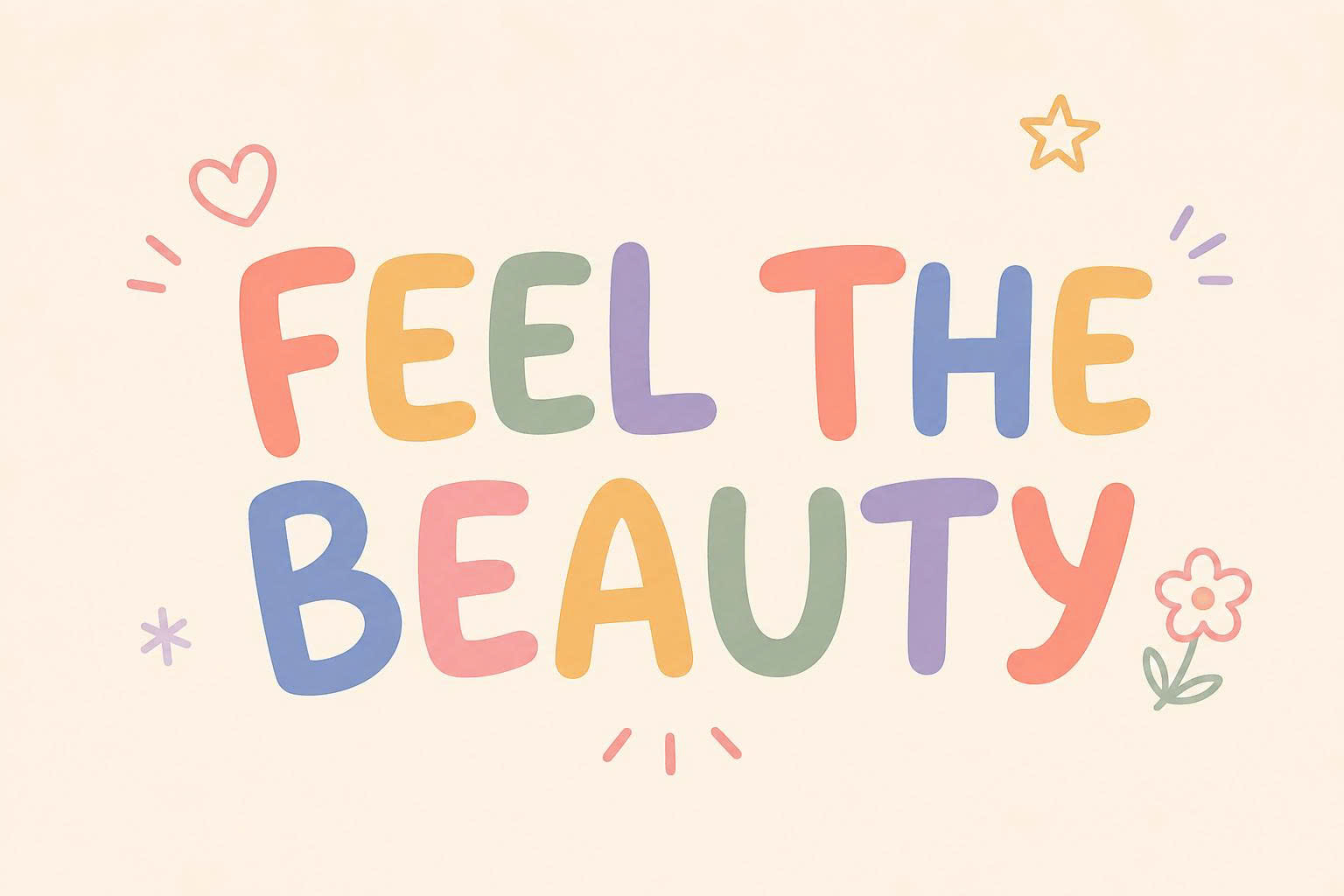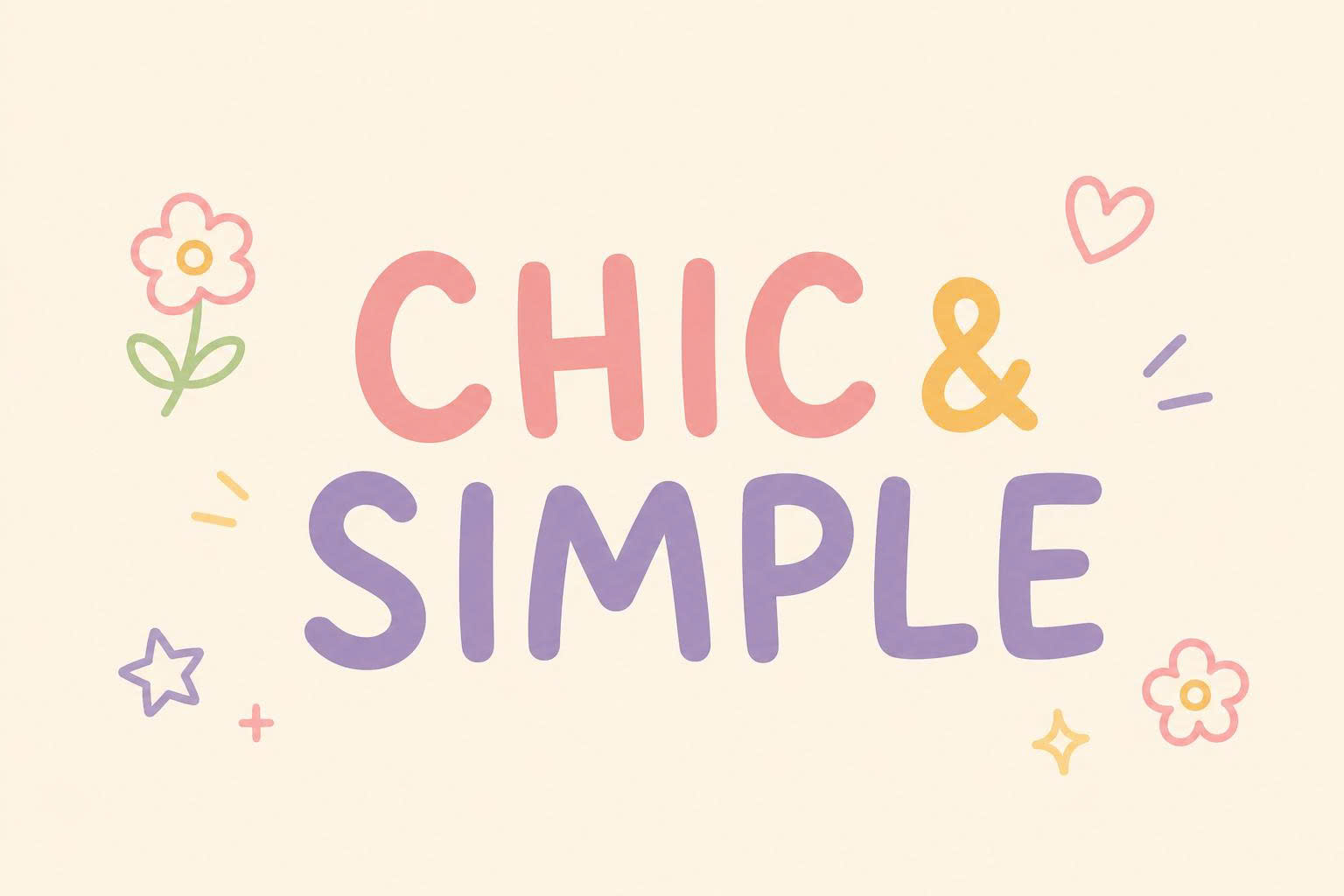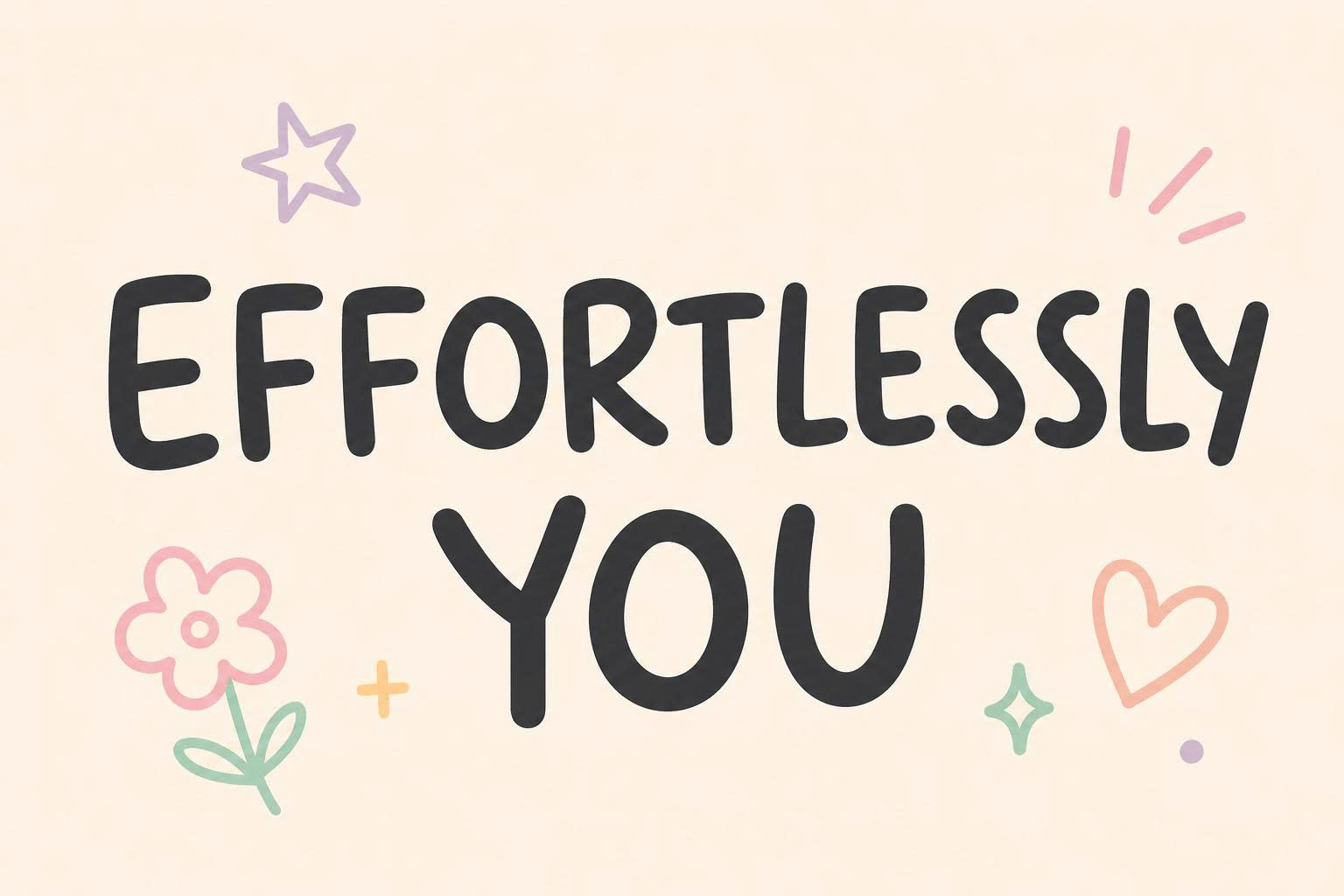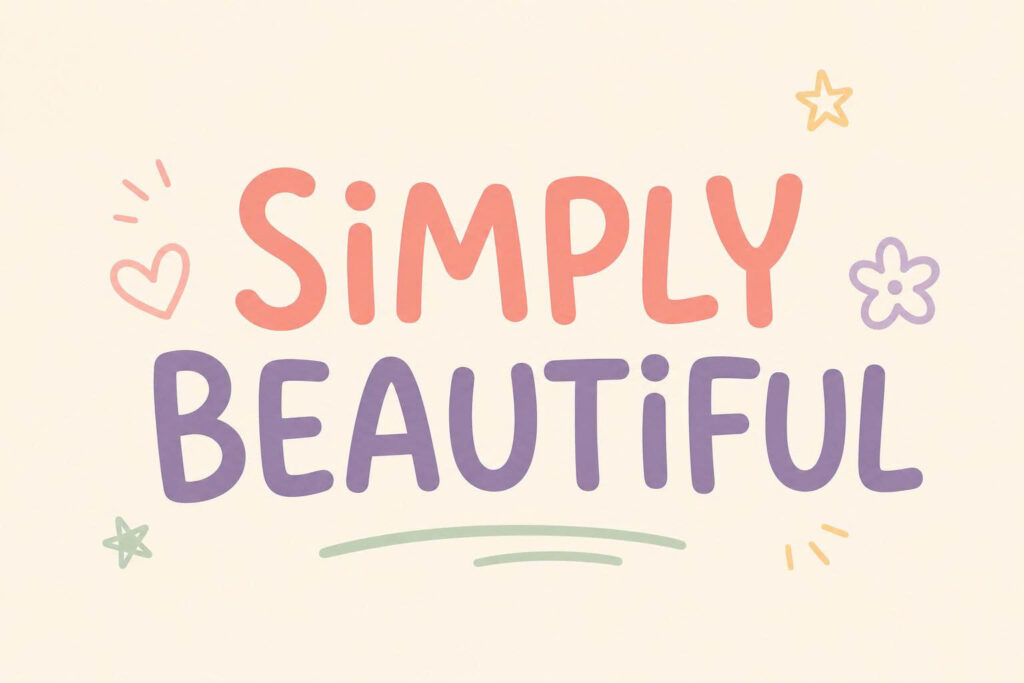
One Little font Việt hóa là bộ phông chữ thuộc dòng Casual Handwritten mang phong cách ngây thơ, mô phỏng sinh động nét viết tay nắn nót của con trẻ trên những trang giấy vẽ thủ công. Với tỷ lệ chữ nhỏ nhắn, các đường bo tròn mềm mại và nhịp điệu chữ tự do, Little One Font là chất liệu trực quan tuyệt vời để các kiến trúc sư, nhà thiết kế mang lại cảm giác ấm áp cho các bản vẽ phối cảnh trường mầm non lắp ghép, phòng ngủ trẻ em hay biển hiệu homestay dành cho gia đình.
Tỷ lệ nhỏ nhắn mộc mạc và nét hồn nhiên của One Little font Việt hóa
Điểm cuốn hút của One Little font Việt hóa nằm ở sự bất đối xứng nhẹ nhàng giữa các con chữ, tạo cảm giác như những lời thủ thỉ yêu thương được ghi chép vội vàng nhưng tràn ngập cảm xúc. Cấu trúc chữ sở hữu độ dày nét thanh thoát, các góc cạnh được gọt tròn mịn màng giúp loại bỏ hoàn toàn sự nghiêm nghị của các khối nhà xây dựng công nghiệp.
Sự ổn định về mặt cảm xúc của dòng font này giúp khơi gợi tình cảm gia đình, sự nâng niu và bầu không khí bình yên trong tổ ấm. Khi kết hợp cùng các vật liệu kiến trúc thân thiện như gỗ thông mộc, vách panel sơn màu pastel, thảm nỉ êm ái hay tường kính đón sáng tự nhiên trong các căn nhà lắp ghép nghỉ dưỡng, One Little Font tạo nên sự hòa quyện thẩm mỹ vô cùng dịu dàng.
Tư vấn từ chuyên viên: One Little Font sở hữu cấu trúc con chữ khá nhỏ và nét thanh thoát. Để bản thiết kế đạt hiệu quả thẩm mỹ tốt, bạn nên sử dụng phông chữ này cho các tiêu đề phụ, câu nhắn gửi yêu thương hoặc tên góc học tập.
03 Ứng dụng Little One Font vào công trình thực tế
Nhờ vẻ ngoài ngây thơ và tính gợi cảm xúc gia đình phong phú, bộ phông chữ này mang lại giá trị thực tế lớn trong khâu tạo điểm nhấn cho các công trình hiện đại:
- Hệ thống biển tên phân khu Trường Mầm non Lắp ghép: Những nét chữ nhỏ nhắn của Little One Font rất ăn ý khi gia công chữ nổi bằng gỗ sáng màu hoặc in decal dán tường, giúp các lớp học mầm non toát lên vẻ ấm cúng và tạo sự an tâm cho phụ huynh khi gửi gắm con trẻ.
- Bảng tên phòng và Biển chào mừng Homestay Gia đình: Phông chữ này khi khắc chìm trên các tấm gỗ pallet mộc sẽ giúp các căn phòng nghỉ dưỡng toát lên nét ngọt ngào, tạo nhiều góc chụp ảnh kỷ niệm ấm áp cho du khách.
- Trang trí góc đọc sách và Không gian phòng ngủ của bé: Bạn có thể dùng One Little font Việt hóa để làm bảng nội quy thân thiện, nhãn dán đồ dùng học tập trong căn hộ lắp ghép, tạo cảm giác ngăn nắp và nuôi dưỡng tình yêu học tập của con nhỏ.
03 Lưu ý bố cục font One Little Font luôn ấm áp và dễ đọc
Để khai thác hiệu quả vẻ đẹp của dòng font viết tay nhỏ nhắn này mà không gây cảm giác vụn vặt cho bản vẽ, người thiết kế nên lưu tâm một số kinh nghiệm sau:
- Kiểm soát kích thước hiển thị: Do cấu trúc chữ có xu hướng nhỏ hơn các phông chữ tiêu chuẩn cùng cỡ, bạn nên tăng kích thước font lên từ 1 đến 2 cỡ (ví dụ từ 12pt lên 14pt) để câu chữ luôn rõ nét khi in ấn trên tài liệu giấy.
- Bố trí khoảng thở tự nhiên: Hãy chừa khoảng trống xung quanh các cụm từ thoáng đãng để nét vẽ hồn nhiên của con chữ có không gian bộc lộ cảm xúc, tránh chèn ép bởi các khung viền kỹ thuật quá cứng nhắc.
- Kết hợp cùng gam màu kẹo ngọt dịu dàng: One Little Font phát huy hiệu quả thị giác cao khi phối cùng các tông màu mang sắc thái êm dịu như hồng phấn, xanh mint nhạt, vàng bơ hoặc kem sữa trên nền tường sáng, làm nổi bật đường nét trong trẻo của bộ chữ.